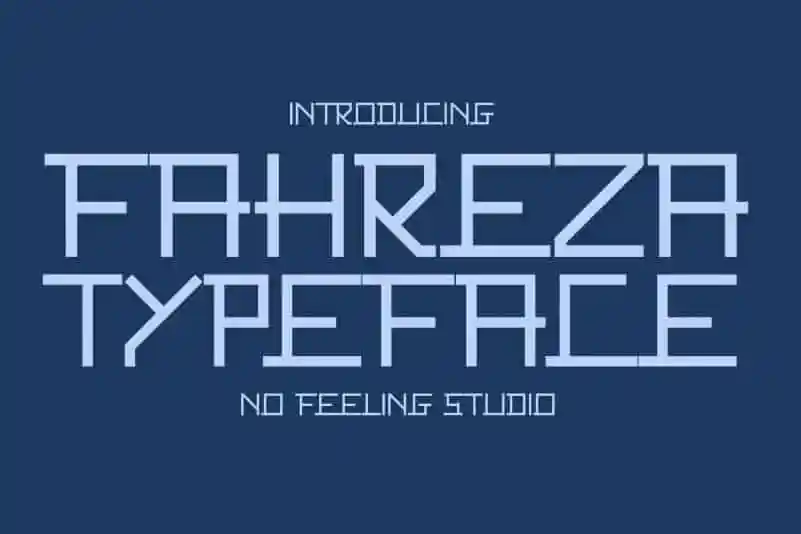
A Fahreza Display Font é uma combinação única de futurista e pixelizada. Esta fonte é perfeita para uma variedade de projetos de marca, logotipos, design criativo, posts nas redes sociais, anúncios e muito mais. Seja criativo com a Fahreza! A sua natureza disruptiva e vibrante torna-a um recurso ideal para qualquer projeto visual desejando algo único e moderno. Ideal para quem procura uma fonte que se destaca e conquista atenção, o seu design futurista dá-lhe um toque especial aos seus projetos. Não importa do tipo de projeto que esteja a lidar com – seja em marketing digital, comunicação visual ou design gráfico, esta fonte é perfeita para manter os olhos se virarem. Todas as suas formas pixeladas criam uma textura única, combinando o estilo minimalista com um toque nostálgico. É a escolha certa para quem procura algo que seja ao mesmo tempo icônico e versátil, adaptável a diversas necessidades de design sem perder seu carácter único. Em resumo, a Fahreza Display é uma ferramenta poderosa no seu portfólio gráfico, prometendo resultados impactantes em qualquer projeto. Não perca esta oportunidade de revolucionar o modo como você visualiza e apresenta suas ideias.